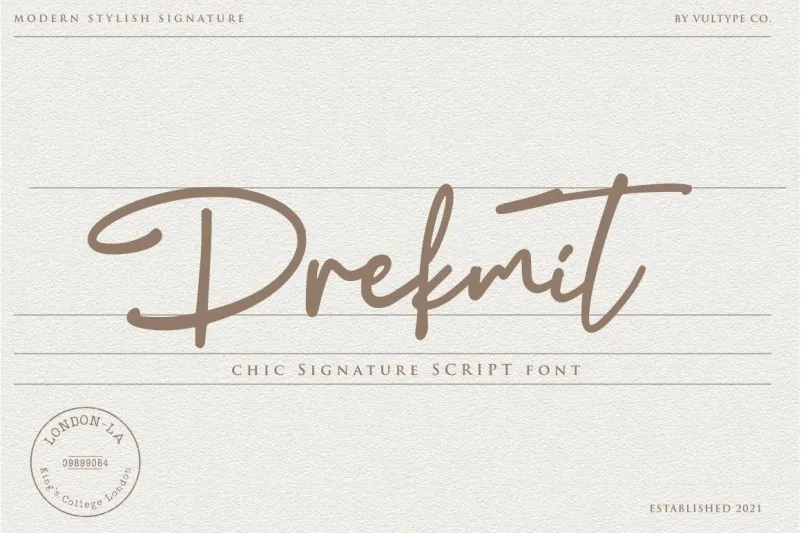
Esta é uma fonte script moderna projetada para imitar perfeitamente a sensação do pen tocando papel. Drekmit foi criado para proporcionar aquele efeito realista que tantos designers amam. Suas formas distintas e única têm um estilo único, quase inigualável, que certamente despertará seu amor pela design gráfico. Utilize-a para criar designs incríveis, uma vez que essa fonte possui a capacidade de trazer vida a qualquer projeto digital ou impresso. Seja você um designer web, em prensa ou simplesmente alguém que cria arte digital, Drekmit é definitivamente a escolha perfeita para quem busca estilo e autenticidade na sua próxima peça visual.